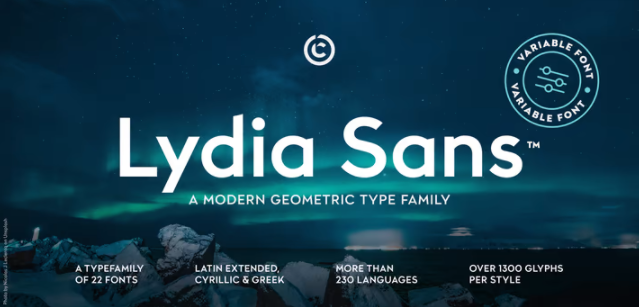
Lydia Sans™ - элегантный геометрический шрифт sans serif с очаровательным профилем и органичным течением. Вдохновленный чистой типографикой 1920-х годов, его характер и разборчивость делают его подходящим для любых текстовых приложений, от дизайна бренда до обширных текстовых макетов.
Lydia Sans™ имеет 22 стиля, переменную шрифтовую технологию, а его весовой диапазон простирается от волосяного начертания до ультражирных форм. Гибкий и адаптируемый, он охватывает 230+ языков, включая расширенные латинскую, кириллическую и греческую системы письма. Имея более 1300 глифов на стиль, система Opentype включает альтернативные формы, маленькие прописные буквы, стандартные и произвольные лигатуры, локализованные формы на латинице и кириллице, формы с учетом регистра, числители и знаменатели, пропорциональные и табличные цифры, косой ноль, дроби и многое другое.
Lydia Sans™ - это система шрифта без засечек для повседневного использования и отличный выбор для широкого круга приложений.